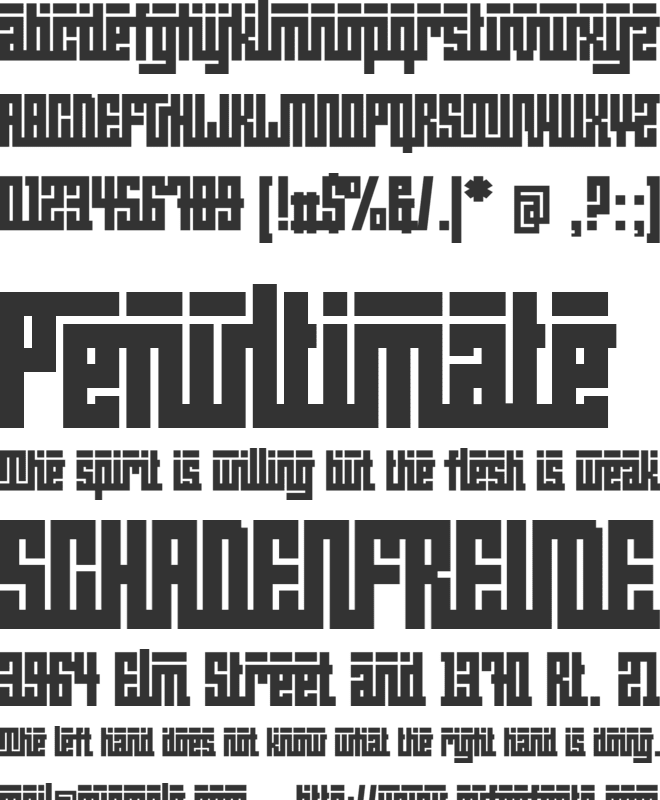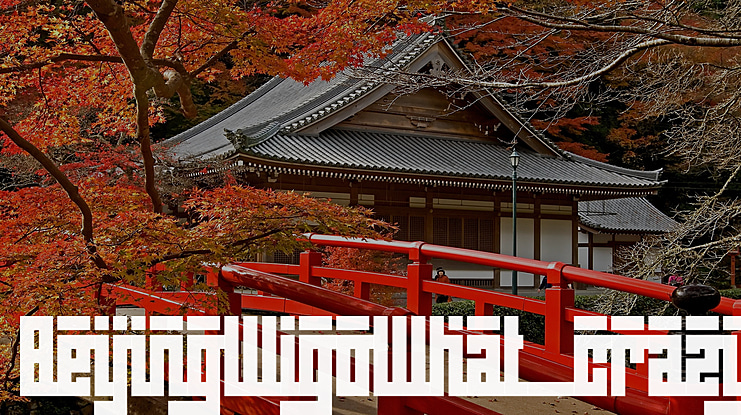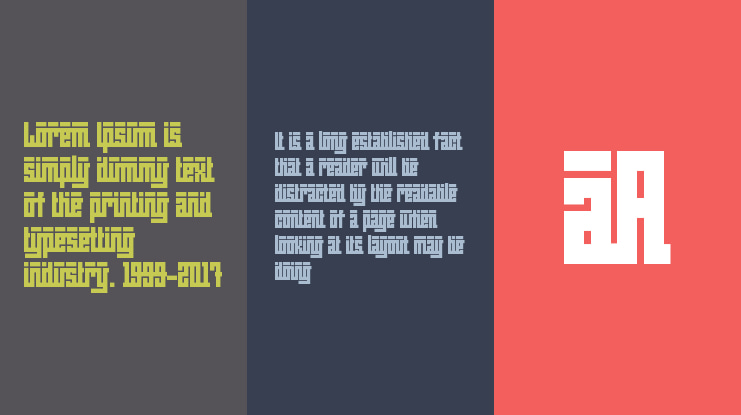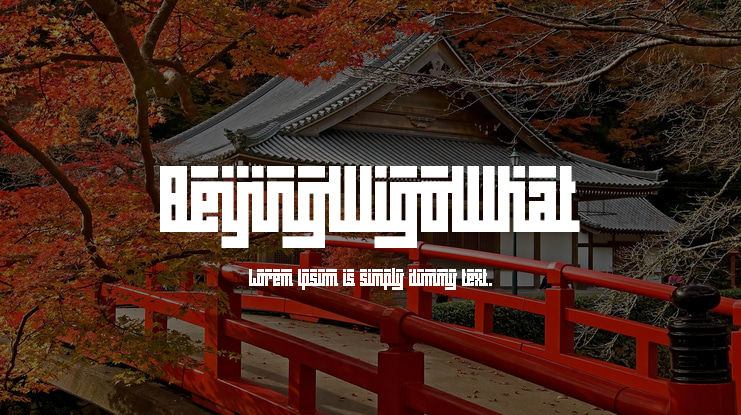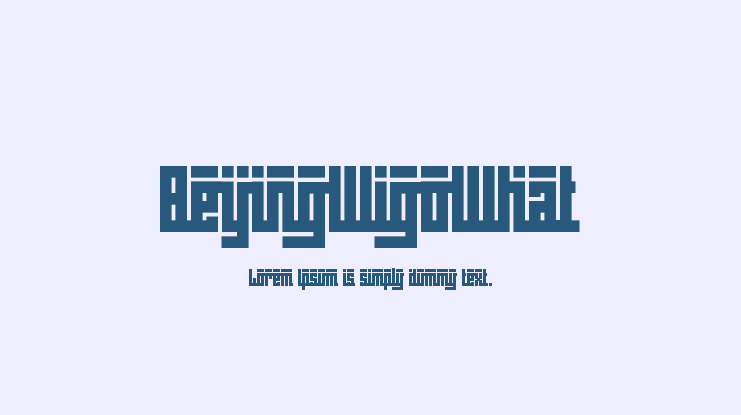
C'est une version ligaturée et modifiée de la police Angie's New House publiée par LeFly Fonts : http://www.vepar.demon.nl/lefly Cette police est sous licence Creative Commons : http://creativecommons.org/licenses/by-sa/2.0/nl/deed.fr
This is a ligatured and modified version of Angie's New House released by LeFly Fonts : http://www.vepar.demon.nl/lefly This font's under Creative Commons license : http://creativecommons.org/licenses/by-sa/2.0/nl/deed.en